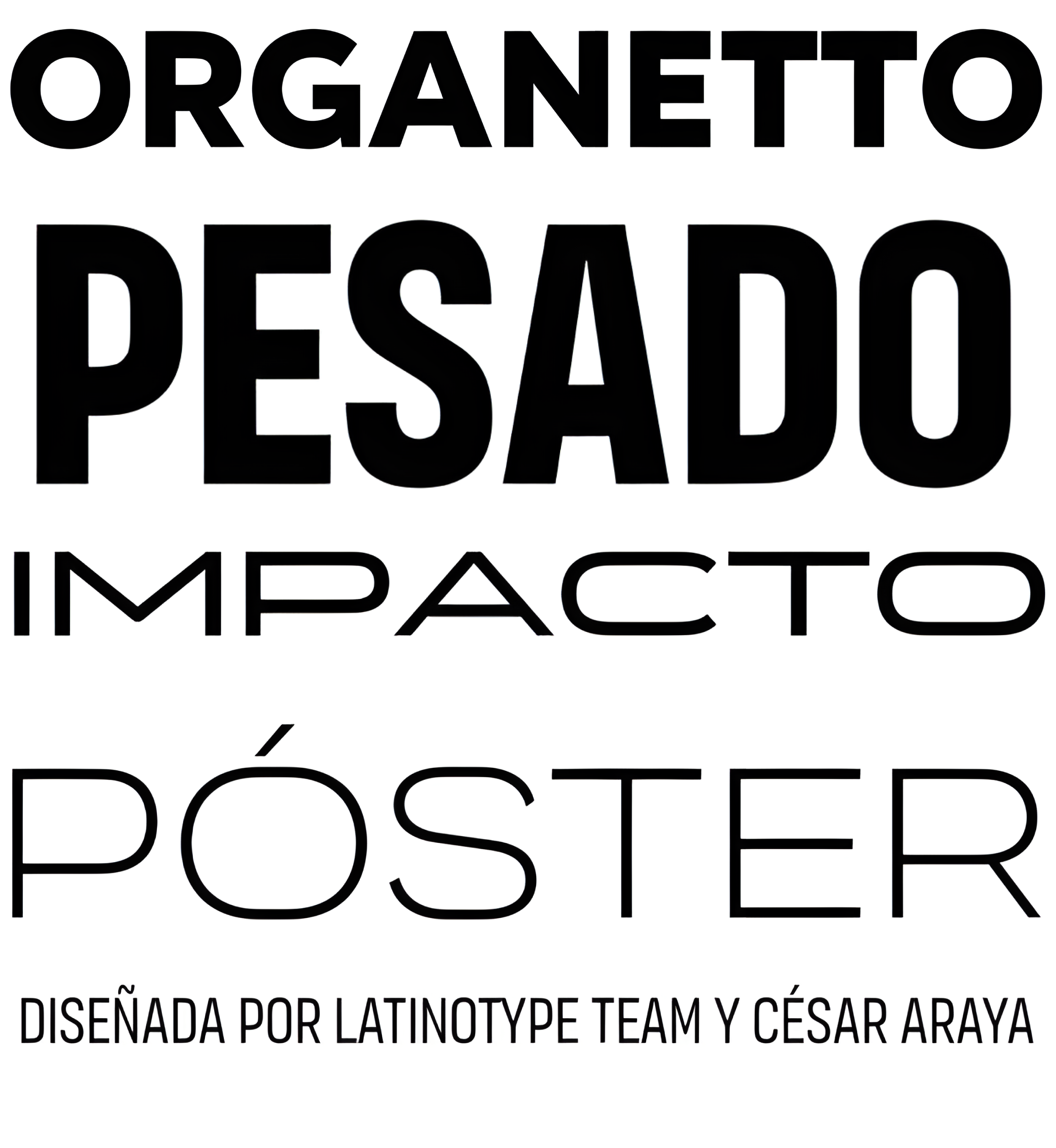
| Año | 2020 |
| Créditos | César Araya |
| Descripción | Organetto es una tipografía inspirada en las letras de los carteles Art Déco, cuyo diseño incorpora la última tecnología tipográfica digital. Esta fuente versátil contiene múltiples anchos que la convierten en una solución ideal para cualquier necesidad de diseño. |
| Familia(s) | Organetto |
| Estilos | 80 |
| Set | Especializado |